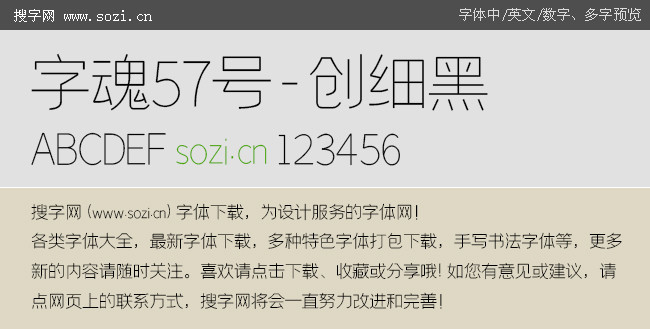
字魂57號-創(chuàng)細(xì)黑
搜字網(wǎng)提供一款字魂57號-創(chuàng)細(xì)黑中文字體下載,該字體是一款基礎(chǔ)黑體字體,該字體包含6763個中文、字母、 符號和數(shù)字,具有古典、中國風(fēng)、現(xiàn)代、優(yōu)雅、簡約 的風(fēng)格,可以滿足您設(shè)計上的各種需求,該字體主要用于屏顯、印章、標(biāo)志、導(dǎo)視、健康養(yǎng)生、電商、媒體、活動 等場景。